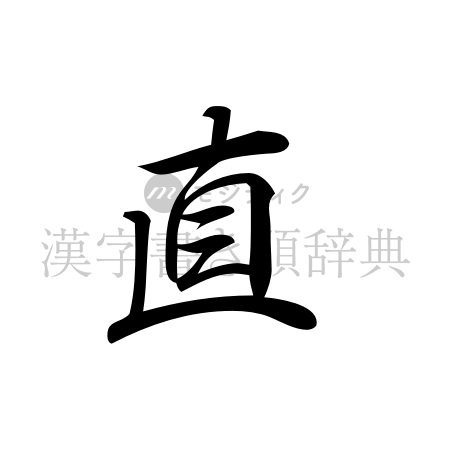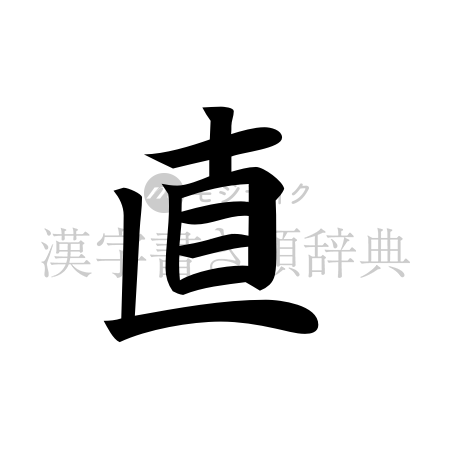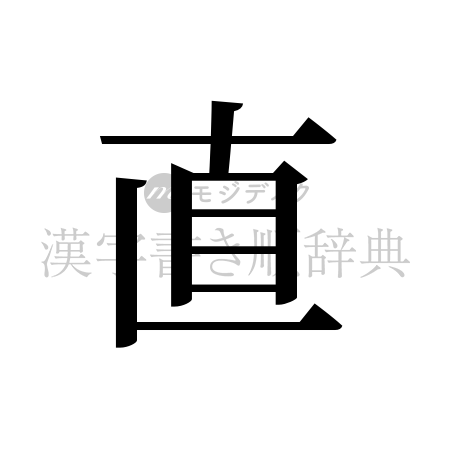
漢字「直」(チョク)の書き順・読み方・意味・部首・画数
「直」の書き順動画アニメーション(8画)
「直」の読み・画数の基本情報
「直」の書体
• 直の書体「ゴシック体」のイメージ
• 直の書体「明朝体」のイメージ
• 直の書体「教科書体」のイメージ
• 直の書体「楷書体」のイメージ
• 直の書体「行書体」のイメージ
• 直の書体「草書体」のイメージ
• 直の書体「隷書体」のイメージ
• 直の書体「篆書体」のイメージ
「直」の意味
• まっすぐであること。
• 正しいこと。
• 直接であること。
• 修理すること。
• すぐに、ただちに。
• 率直であること。
• 正直であること。
• 直角のこと。
• 直線のこと。
• 直立すること。
「直」の意味の英訳
漢字は1文字で多様な意味を持ちますが、「直」を英語で表す場合、一般的には straightaway, honesty, frankness, fix, repair などがあります。
「直」の成り立ち・由来
六書分類 会意文字
構造 目+縦線(十)+隠す意の符
「直」は会意文字です。古い字形は「目」の上にまっすぐな縦線を引き、目でまっすぐに見ることを表しました。のちに、隠れたものを見つけ出すという意を添える形が加わり、現在の「十」と「目」を組み合わせた字形へと整えられました。まっすぐに見る、曲がっていないことから、「まっすぐ」「正しい」「率直」の意となり、さらに「ただちに」「直接」といった意味にも広がりました。目を軸に、ゆがみなくまっすぐ見通す様子をかたどった字です。
※ 細部の字形解釈には諸説あります。
「直」を含む熟語・単語とその意味
直線 - ちょくせん
まっすぐな線。
直進 - ちょくしん
まっすぐにすすむこと。
直情 - ちょくじょう
偽ったり飾ったりしない、ありのままの感情。